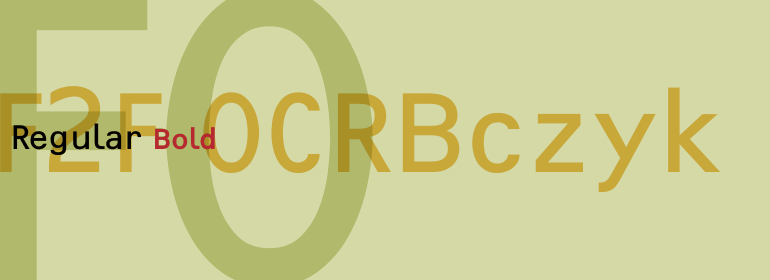
F2F OCRBczyk™
字体品牌: Linotype(Monotype) 设计师:Branczyk,Alexander 字体分类:无衬线体、正文字体 字体属性:外文 字符集:Unicode 发布时间: 2018
原始的OCR B是为光学字符识别系统设计的,因此是等距的。设计师Alexander Branczyk制作了更具印刷体味和合身性的版本,既有常规砝码,也有粗体砝码,并将其称为OCRBczyk™。
The original OCR B was designed for optical character recognition systems and was therefore monospaced. Designer Alexander Branczyk made a more typographically tuned and fitted version, with both regular and bold weights, and called it OCRBczyk™.